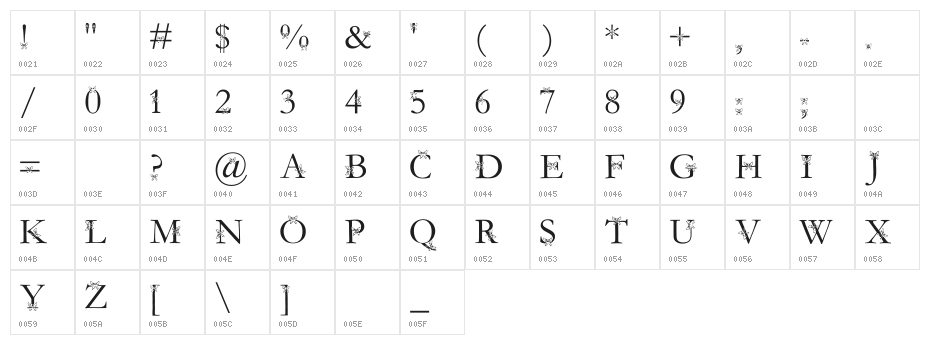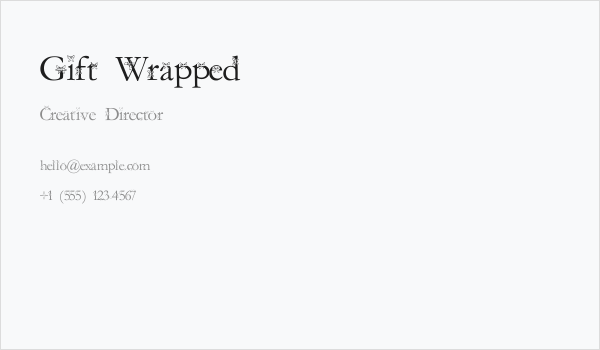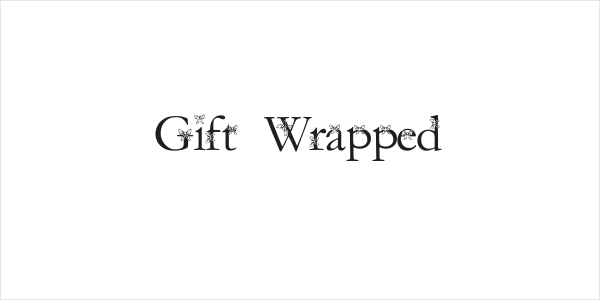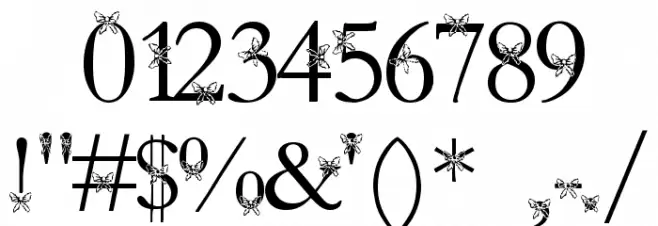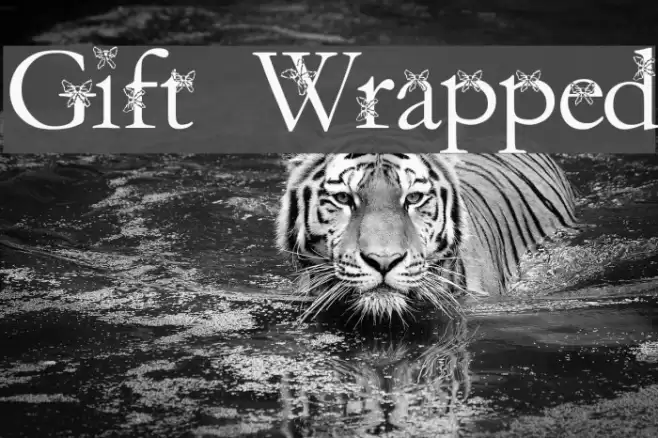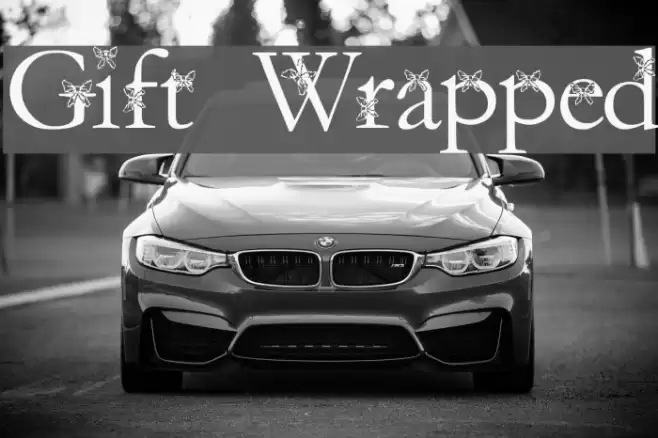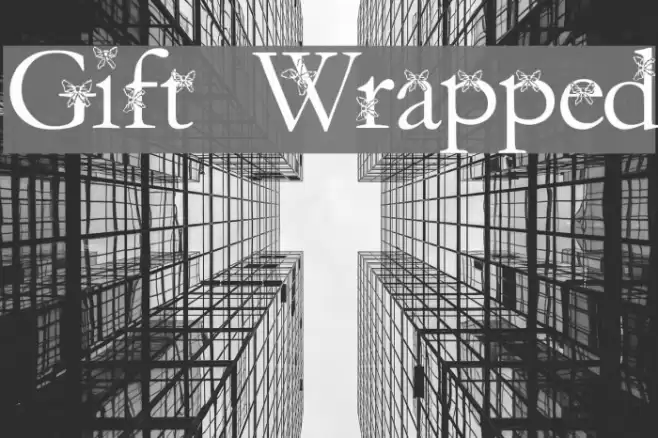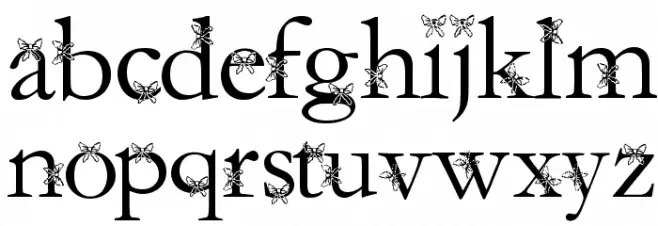
Gift Wrapped Font
✎ Decorative
| Anwendungsfall | Headlines, Invitations, Greeting Cards |
| Vorgeschlagene Projekte | Ideal for wedding invitations, holiday cards, festive banners, and any design requiring a celebratory and elegant touch. |